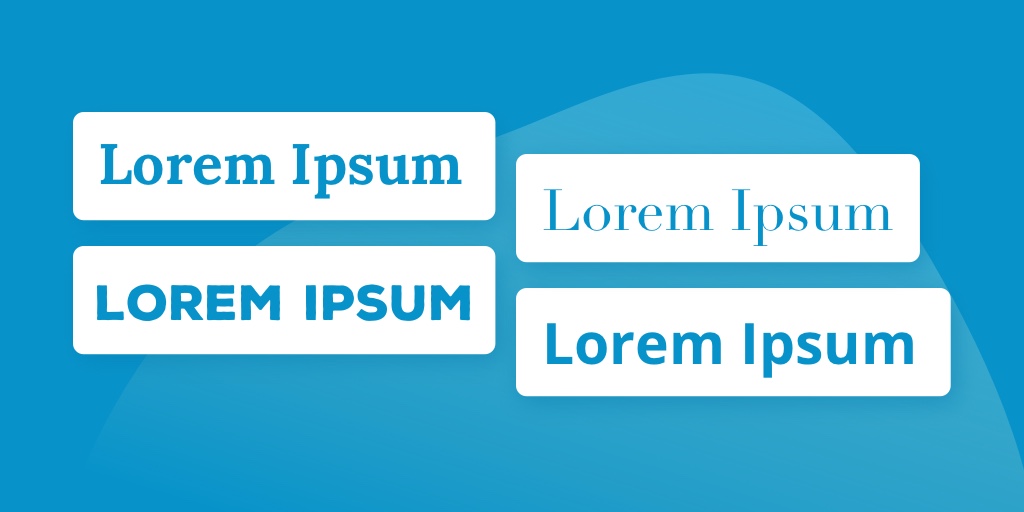
글꼴 심리학 101: 글꼴로 감정 만들기
당신이 보는 모든 것이 감정적 반응을 일으킨다는 것을 알고 계셨습니까? 그것을 보는 방법과 장소 또한 그 감정적 반응에 추가됩니다.
이미지에 대한 이러한 심리적 반응은 마케팅의 강력한 도구입니다. 좋아하는 브랜드가 이 사실을 알고 이러한 세부 사항을 염두에 두고 로고, 포장 및 그래픽을 디자인할 가능성이 있습니다!
그리고 가장 중요한 세부 사항 중 하나는? 글꼴!
글꼴 선택은 작은 감자 튀김처럼 보일 수 있지만 각각 고유 한 개성이 있습니다!
우아한 글꼴을 선택하든 재미있고 현대적인 서체를 선택하든 청중에게 신호를 보내는 것입니다. 이러한 단서는 청중이 브랜드로서 귀하가 누구인지 이해하는 데 도움이 됩니다.
그것이 마케팅에서 글꼴의 심리학의 힘입니다!
이러한 미묘한 글꼴 의미와 힌트를 직접 활용하는 방법을 배우고 싶으십니까? 글꼴로 감정을 만드는 방법을 알아 보려면 계속 읽으십시오!
글꼴이란 무엇입니까?
가장 먼저 할 일은 글꼴이란 무엇입니까? 누구에게 묻느냐에 따라 다른 대답을 얻을 수 있지만 기본적으로 글꼴은 특정 크기, 두께 및 서체 스타일입니다 .
글꼴 정의는 특정 문자, 숫자 및 단어가 어떻게 보이는지 생각할 수 있습니다!
그러나 우리는 당신이 무엇을 생각하고 있는지 알고 있습니다 ...
글꼴과 서체의 차이점은 무엇입니까?
많은 경우 "글꼴"과 "서체"라는 단어는 같은 의미로 사용되지만 약간의 차이가 있습니다.
서체 ("글꼴 패밀리"라고도 함) 글꼴은 해당 서체의 특정 변형인 반면 일반적인 스타일과 문자 모양입니다.
예를 들어 Times New Roman을 사용하십시오! Times New Roman은 서체입니다. Times New Roman Italic 및 Times New Roman Bold 는 모두 해당 서체에 포함된 글꼴입니다!
"글꼴"은 이 두 가지의 축약형으로 자주 사용되는 스타일 정의이지만 특히 디자이너와 채팅할 때 차이점을 아는 것은 문제가 되지 않습니다!
4가지 유형의 글꼴 스타일
세계에는 수천 개의 글꼴과 서체가 존재하며 크리에이티브와 브랜드는 매일 그 숫자에 추가되고 있습니다!
모든 작은 변형은 새롭고 독창적인 글꼴로 간주될 수 있습니다.
목록을 좁히고 정렬하는 데 도움이 되도록 일반적으로 글꼴이 속하는 네 가지 기본 범주가 있습니다.
- 세리프체
- 산세리프체
- 스크립트 글꼴
- 글꼴 표시
Slab Serifs와 같은 추가 범주 가 있지만 이러한 네 가지 기본 사항을 알고 있으면 각각의 특성을 인식하고 설계에서 정보에 입각한 결정을 내리는 출발점이 될 것입니다.
아래에서 더 이야기합시다!
세리프체
세리프는 문자의 주요 모양에 연결된 작은 선(또는 획)입니다. 다음 위치에서 "작은 발"처럼 보일 수 있습니다.
- 문자 A 또는 R의 하단에
- H 또는 U 상단의 짧은 수평선
- D 또는 B의 수직선 너머로 뻗어 있는 작은 컬.
이러한 멋진 부록이 있는 모든 글꼴은 세리프 글꼴입니다. 세리프 문자의 선 너비는 스타일적으로도 다를 수 있습니다! 예를 들어, 세리프체 O의 선은 측면에서 더 넓고 상단에서 더 좁을 수 있습니다.
그리고 serif 글꼴은 매우 다른 너비의 선을 가질 수 있습니다.
산세리프체 글꼴
Sans는 프랑스어로 '없는'이라는 뜻입니다. 따라서 sans serif 글꼴은 "serif가 없는" 모든 것입니다. 즉, serif 글꼴의 확장 기능이 부족합니다.
발도, 약간의 스트로크도, 확장도 없습니다. Sans serif 글꼴은 일반적으로 각 개별 문자 전체에 걸쳐 보다 일관된 획 크기를 갖습니다.
스크립트 글꼴
스크립트 글꼴은 마치 손글씨처럼 보이는 것입니다.
실제 필기체 스타일의 레터링, 서예일 수도 있고 단순히 곡선형, 원형, 비스듬한 또는 연결 문자로 특징지어질 수도 있습니다.
복잡하거나 캐주얼한 스크립트 글꼴은 일반적으로 serif 또는 sans serif 글꼴보다 더 독특하고 분명히 개인화되어 눈에 띕니다.
글꼴 표시
디스플레이 글꼴은 모든 모양과 크기로 제공되며 위에 나열된 유형 중 하나일 수 있습니다. 예를 들어, "Vintage Dreams"는 스크립트 글꼴이자 디스플레이 글꼴입니다.
특정 속성 대신 표시 글꼴은 주의를 끄는 헤더 또는 독립 실행형 문장 텍스트와 같은 목적에 따라 정의됩니다.
이 컨텍스트에서 사용하도록 설계되었으며 더 작은 단락이나 더 긴 사본에 사용하기에는 거의 항상 부적절합니다.
이러한 이유로 디스플레이 글꼴은 효과를 위해 드물게 사용해야 합니다!
감성을 불러일으키는 글꼴
색상 팔레트 및 모양과 마찬가지로 글꼴은 매우 다른 감정을 불러일으킬 수 있습니다.
이것이 그들이 당신에게 당신의 메시지에 대한 많은 권한과 통제력을 제공하는 방법입니다!
Coca-Cola는 포장에 "원래 맛" 및 "1886년 이후"와 같은 컨텍스트 단서를 인쇄하지만, 그 감정은 유산에 스며든 전통적인 스크립트 로고에 의해 실제로 집으로 돌아갑니다.
반면에 나이키의 대담한 산세리프 로고는 날렵하고 강력하며 깨끗한 실루엣으로 현대 운동선수의 정신을 이상화하여 보여줍니다.
사용되는 글꼴 유형은 브랜드를 강화하는 데 도움이 될 뿐만 아니라 그것이 만들어내는 감정적 반응은 행동을 불러일으키고 충성도를 심화시킬 수 있습니다. 그리고 이것은 모두 잠재 의식 수준에서 이루어집니다!
결론은 적절하게 사용하면 감성적인 글꼴이 마케터가 목표를 달성하는 데 도움이 될 수 있다는 것입니다.
세리프체의 심리학
글꼴의 심리를 살펴보면 New York Times에서 볼 수 있는 것과 같은 세리프 글꼴은 즉시 형식, 신뢰성 및 권위를 느낄 수 있습니다. 그들은 따뜻하고, 환영하고, 존경받을 만하고, 성숙하고, 화려하거나 사치스러운 경향이 있습니다.
Serif 글꼴은 종종 다음과 같은 감정을 불러일으킵니다.
안정적인, 형식적인, 전통적, 권위 있는, 존경할 만한, 세련된, 고전적인, 비싼
로고 예:
티파니, 소니, 메르세데스-벤츠, 갭
산세리프체의 심리학
Helvetica 및 Arial과 같은 Staple sans serif 글꼴은 시각적 기본값이 되었습니다.
Impact와 같은 글꼴은 소셜 미디어 그래픽에서도 자주 볼 수 있습니다. 즉, 눈에 덜 띄지만 다른 옵션에서는 볼 수 없는 방식으로 대담하고 현대적이며 간단할 수도 있습니다.
사실, 이것이 산세리프체를 다재다능한 옵션으로 만드는 이유입니다. 필요할 때 눈에 띄거나 디자인에 눈에 거슬리지 않게 혼합할 수 있습니다.
산세리프체는 종종 다음과 같은 감정을 불러일으킵니다.
심플, 심플, 시크, 모던, 클린, 미니멀, 다재다능
로고 예:
나이키, 구글, 맥도날드, 페덱스
스크립트 글꼴의 심리학
감정을 불러일으키는 글꼴을 생각할 때 우리는 종종 스크립트 글꼴에 끌립니다.
그들은 다양한 감정을 불러일으킬 수 있으며 산세리프체 글꼴이 지배적인 것처럼 보이는 세상에서 더 기억에 남는 경향이 있습니다.
캐주얼하거나, 우아하거나, 독특하거나, 형식적인 것을 찾고 있든 간에 스크립트 글꼴은 매우 효과적일 수 있습니다.
스크립트 글꼴은 종종 다음과 같은 감정을 불러일으킵니다.
여성적, 창의적, 개인적, 섬세함, 여유로움, 예술적, 감상적, 로맨틱
로고 예:
코카콜라, 켈로그, 포드, 버드와이저
디스플레이에 사용되는 글꼴의 심리학
디스플레이 글꼴은 주의에 관한 것입니다. 그들은 크게 다르며 실제로 한 가지 공통점이 있습니다. 그들은 배경 가수가 아니라 슈퍼스타라는 것입니다.
자주 사용해서는 안 되며 본문에 표시되지 않아야 합니다. 그러나 잘 사용하면 시선을 사로잡고 사람들을 끌어들이는 매우 구체적인 목표를 달성합니다.
디스플레이 글꼴은 종종 다음과 같은 감정을 불러일으킵니다.
기발한, 친근한, 독특한, 표현적인, 최신 유행의, 흥미 진진한, 재미있는
모든 것을 함께: 그 글꼴은 무엇입니까?
말은 결코 단순한 말이 아닙니다. 그들이 말하는 것 이상으로 메시지를 전달합니다.
단어의 의미는 한 가지입니다. 외모와 스타일이 불러일으키는 감정은 모두 다른 것이 될 수 있습니다!
대부분의 브랜드와 대부분의 최고 마케터의 목표는 이 모든 것을 하나의 강력한 패키지로 통합하는 것입니다.
이 중 일부는 예술입니다. 그 중 일부는 과학, 보다 구체적으로 심리학입니다. 모든 뉘앙스와 미묘한 메시지가 청중에게 전달되는 방식을 알 수 있다면 완전히 새로운 사고 방식을 활용할 수 있을 것입니다.
정말 간단한 글꼴로 감정을 만들 수 있습니다! 그리고 귀하의 캠페인과 메시지는 훨씬 더 강력해질 것입니다.